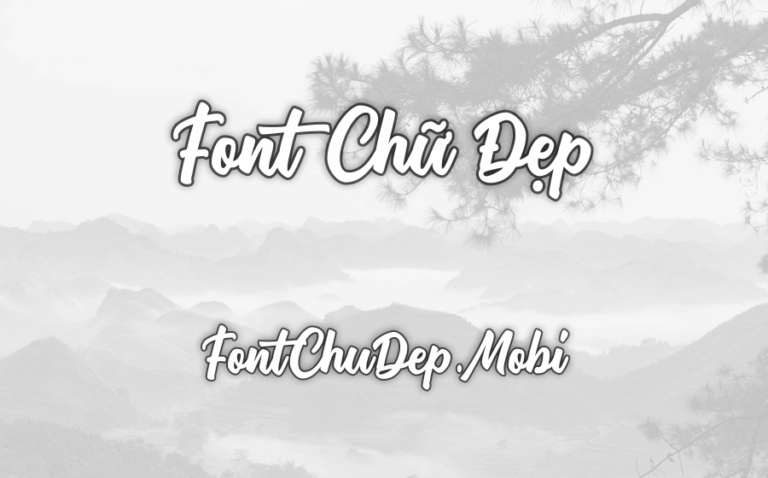
Font Acryle Script là một kiểu chữ viết tay với phong cách thư pháp đương đại, được thai nghén bởi Måns Grebäck và ra mắt năm 2014. Với những đường nét uyển chuyển và đầy tinh tế, font này mang lại cho thiết kế của bạn một vẻ đẹp thanh lịch và nghệ thuật.
Đặc biệt, phiên bản Acryle Script đã được Mộc Hạ Việt hóa, hỗ trợ trọn vẹn tiếng Việt cùng hơn 64 ngôn ngữ khác như Anh, Pháp, Tây Ban Nha, Đức, Ý và Bồ Đào Nha. Điều này mở rộng khả năng ứng dụng của font trong việc thiết kế đa ngôn ngữ một cách dễ dàng. Acryle Script đã được các thành viên của FontChuDep.mobi sưu tầm và chia sẻ, đáp ứng một cách tuyệt vời nhu cầu của cộng đồng thiết kế. Với những ký tự mềm mại và đặc trưng, cùng với ligatures độc đáo, font này rất lý tưởng cho việc thiết kế logo, thiệp mời, bao bì sản phẩm, và các ấn phẩm quảng cáo.
Những lĩnh vực như quảng cáo, giáo dục, công nghệ và ẩm thực đều có thể tận dụng font này để tạo ra các tác phẩm thiết kế cuốn hút và ấn tượng. Khi bạn muốn truyền đạt thông điệp một cách rõ ràng mà vẫn giữ được vẻ nghệ thuật và sang trọng, Acryle Script chắc chắn sẽ là sự lựa chọn hoàn hảo.